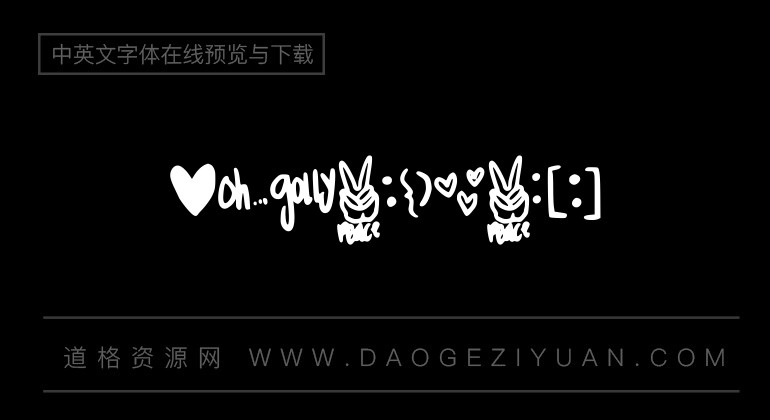
MeganBats
MeganBats 是一款由 Megan Fox 创作的字体,它是一款具有明显个人风格的手写字体,具有独特的笔画形状,让您的文本充满活力和个性。它有着轻松、活泼、可爱的风格,适合用于海报、卡片、T恤、礼品等。它还具有一些有趣的替换字符,可以让您的文字更加有趣和生动。
MeganBats是一款非常不错的手写艺术字体,具有很好的视觉感,适合于文化类的宣传设计、商业类品牌的广告和产品包装设计以及个性化文字排版等较多场景。